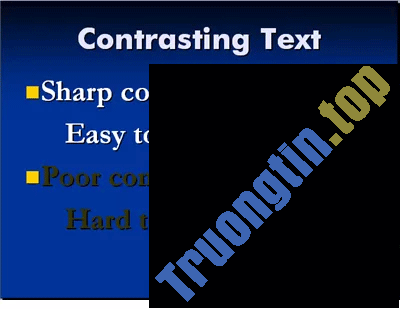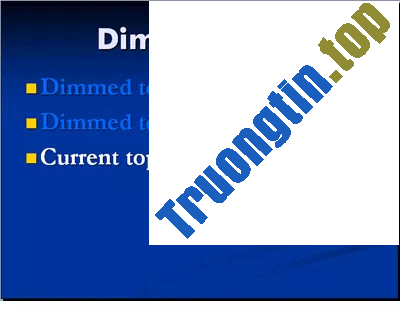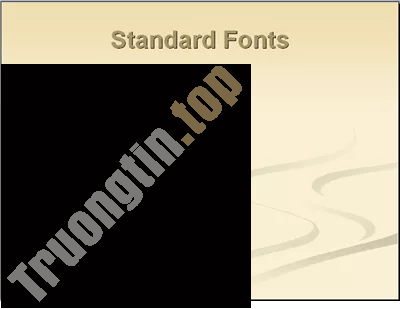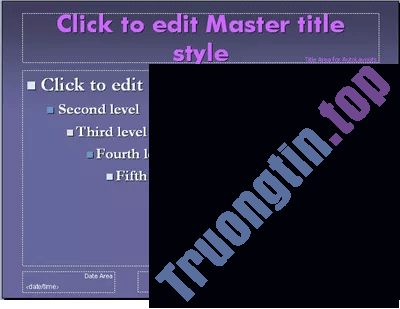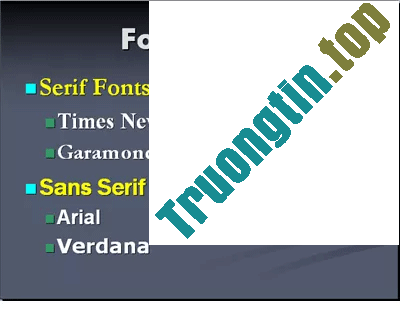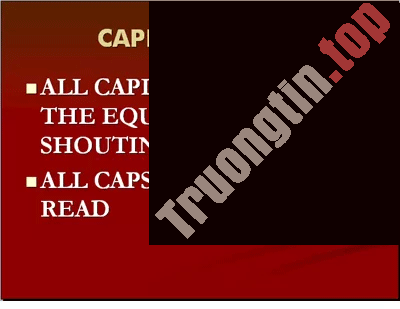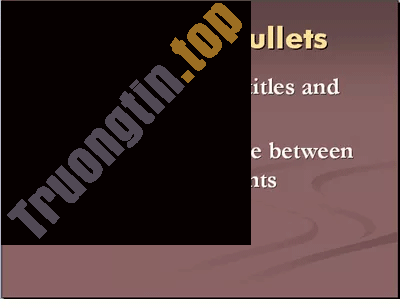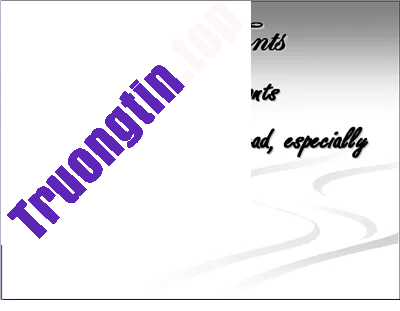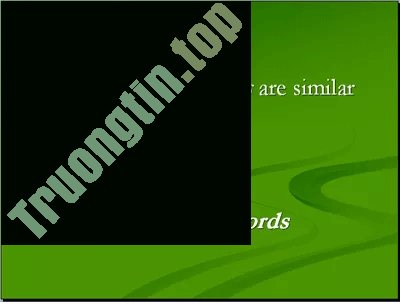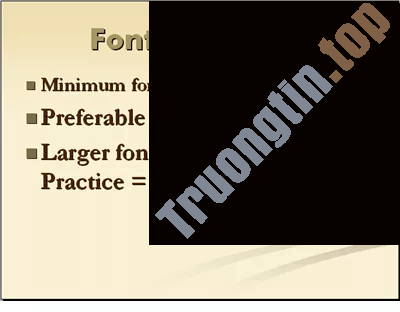
Văn bản là một phần quan trọng trong bài thuyết trình PowerPoint. Vậy làm ra sao sử dụng font chữ hiệu quả? Hãy cùng điểm qua một số mẹo sử dụng font chữ trong file PowerPoint nhé.
Mẹo sử dụng font chữ trên PowerPoint
- 1. Tương phản giữa font chữ và background
- 2. Sử dụng font chữ chuẩn
- 3. Tính nhất quán làm bài thuyết trình đẹp hơn
- 4. Loại font chữ
- 5. Không sử dụng tất cả chữ in hoa
- 6. Sử dụng font chữ không trùng lặp cho tiêu đề và các gạch đầu dòng
- 7. Tránh các kiểu font chữ viết tay
- 8. Hạn chế sử dụng chữ in nghiêng
- 9. Để font chữ với kích cỡ lớn
- 10. Sử dụng tính năng làm mờ văn bản
1. Tương phản giữa font chữ và background
Điều đầu tiên và quan trọng nhất về việc sử dụng font chữ trong bài thuyết trình là đảm bảo sự tương phản đậm nét giữa màu font chữ trên slide và màu nền slide.
2. Sử dụng font chữ chuẩn
Bám sát font chữ phổ biến cho mọi máy tính. Nếu sử dụng font chữ dù tuyệt đến đâu nhưng vẫn không được cài đặt trên máy tính thì nó cũng bị thay thế bằng font chữ khác và có thể làm lệch định dạng của bạn trên slide.
Chọn font chữ phù hợp với bài thuyết trình. Nếu bài thuyết trình nhắm đến trẻ nhỏ, bạn nên sử dụng font chữ trông vui nhộn, bắt mắt. Nếu bài thuyết trình cần sự trang trọng, bạn nên lựa chọn font chữ đơn giản. Tuy nhiên nếu font chữ chọn không được cài đặt trên máy tính trình bày, bạn phải đảm bảo nhúng đúng font chữ vào bài. Mặc dù điều này sẽ tăng kích thước file của bài thuyết trình nhưng ít nhất bạn cũng đảm bảo nó xuất hiện như dự định.
3. Tính nhất quán làm bài thuyết trình đẹp hơn
Bạn chỉ nên sử dụng hai hoặc nhiều nhất là ba font chữ cho toàn bộ bài thuyết trình. Sử dụng slide master trước lúc nhập văn bản để thiết lập font chữ đã chọn trên slide, giúp tránh thay đổi từng slide riêng lẻ.
4. Loại font chữ
Serif là loại font chữ có đuôi nhỏ gắn liền với mỗi chữ. Times New Roman là ví dụ về loại font chữ này. Những font chữ này dễ đọc nhất trên slide với nhiều chữ mặc dầu không nên bỏ nhiều chữ trên slide khi thực hành bài thuyết trình PowerPoint. Báo và tạp chí sử dụng font chữ serif để dễ đọc.
Sans serif là loại font chữ dễ dàng nên phù hợp sử dụng cho tiêu đề của slide. Một số loại font chữ Sans serif là Arial, Tahoma và Verdana.
5. Không sử dụng mọi thứ chữ in hoa
Tránh sử dụng mọi thứ các chữ in hoa trên slide, ngay khi cho những tiêu đề vì cực khó đọc.
6. Sử dụng font chữ khác nhau cho tiêu đề và các gạch đầu dòng
Chọn font chữ khác nhau cho tiêu đề và các gạch đầu dòng để khiến các slide văn bản thú vị hơn. In đậm chữ khi cần để dễ đọc.
7. Tránh các kiểu font chữ viết tay
Tránh các kiểu font chữ như chữ viết tay vì những loại font chữ này không dễ đọc. Trong phòng tối và đặc biệt khi ngồi ở cuối phòng, khán giả hầu như không thể đọc được chữ.
8. Hạn chế sử dụng chữ in nghiêng
Tránh sử dụng chữ in nghiêng trừ khi thực sự cần có và sau đó đảm bảo bôi đậm văn bản đó để nhấn mạnh. Chữ in nghiêng cũng gây nên vấn đề tựa như như font chữ viết tay, khiến khán giả khó đọc chữ trên slide.
9. Để font chữ với kích thước lớn
Không sử dụng font chữ nhỏ hơn 18pt, tốt nhất để 24pt làm font chữ tối thiểu. Font chữ có kích thước lớn hơn chẳng những lấp đầy slide, để ít khoảng trống mà còn hạn chế chữ trên đó. Quá nhiều chữ trên slide cho biết bạn là người mới làm bài thuyết trình.
Lưu ý: Không phải kích cỡ font chữ nào cũng như nhau. Font chữ 24pt là vừa với Arial nhưng nhỏ với Times New Roman.
10. Sử dụng tính năng làm mờ văn bản
Sử dụng tính năng làm mờ văn bản cho các gạch đầu dòng. Điều này giúp khán giả tập trung vào vấn đề hiện tại vẫn đang trình bày.